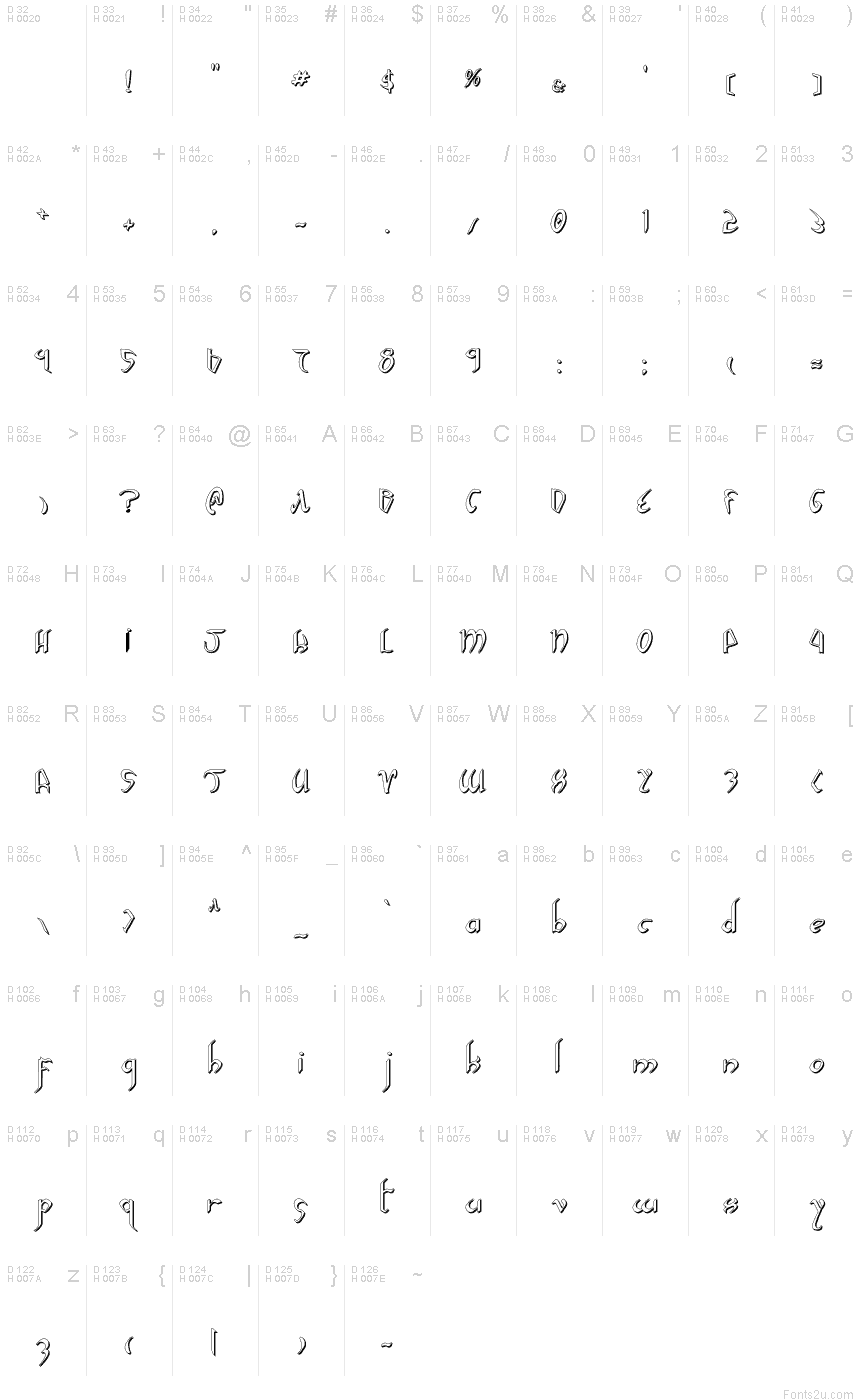
Anteprima del carattere Xaphan II Shadow
Xaphan II Shadow di Iconian Fonts è un font gotico celtico gratuito dal carattere medievale affilato, con un'ombra integrata che dona alle lettere un effetto di metallo inciso. Grazie ai tratti appuntiti, divisi e alle estremità ricurve simili a corna, questo font trasmette un senso rituale e arcaico, piuttosto che un semplice aspetto decorativo.
È ideale per copertine di libri fantasy, loghi di giochi, grafiche di band, titoli di poster e packaging a tema dove serve un font gratuito capace di creare subito un'atmosfera medievale senza risultare una semplice stranezza. Usalo per titoli brevi, schermate di presentazione o iniziali in stile monogramma: le forme ombreggiate e i dettagli uncinati creano l'atmosfera da soli.